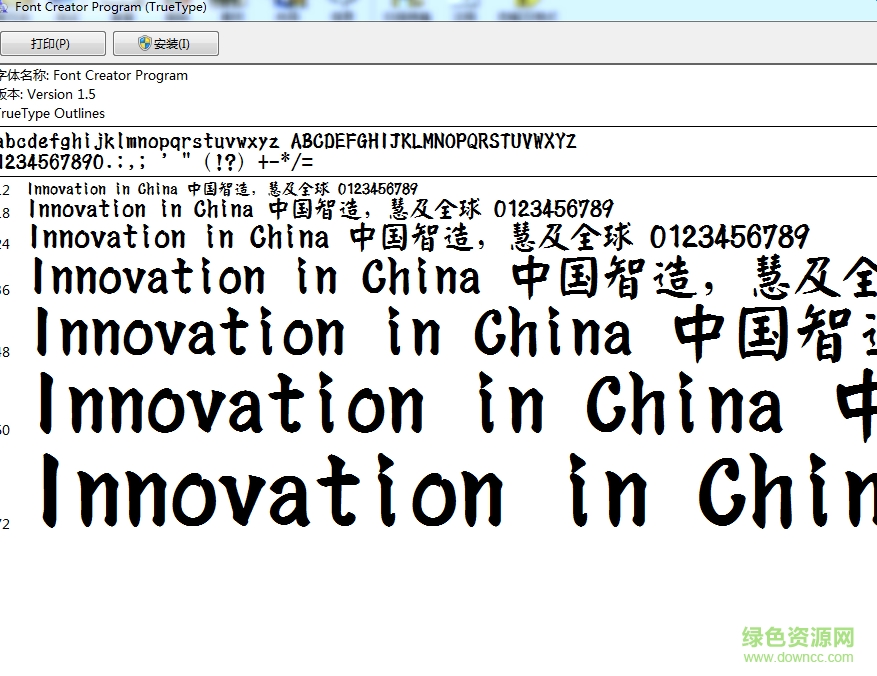
汉仪颜楷简字体
汉仪颜楷简体是一款汉仪类颜值文雅风格字体软件,颜楷体以楷书的优美搭配浓浓的笔画,整体效果非常好看醒目,适用于各大海报广告标题的应用,还有更多好看的字体欢迎来绿色资源网下载使用!
汉仪颜楷简体是一款应用于艺术设计方面的简体中文字体,该字体笔画粗壮,尾部的甩尾有力且有丰富的笔触细节,大字效果突出且引人注目;并且最大程度还原作者书写字形,细节表现完整,且字库完整,可以广泛应用于名片设计、新闻媒体、宣传海报、ppt、影视制作以及内容用字等领域。
此字体笔画细腻行如流水,完美展现现代楷体的正式风格,现代气息十足,整体效果比较工整好看,此字体老女老少皆宜使用!
颜楷体简直太帅了,跟人聊天颇有成就感,哈哈!